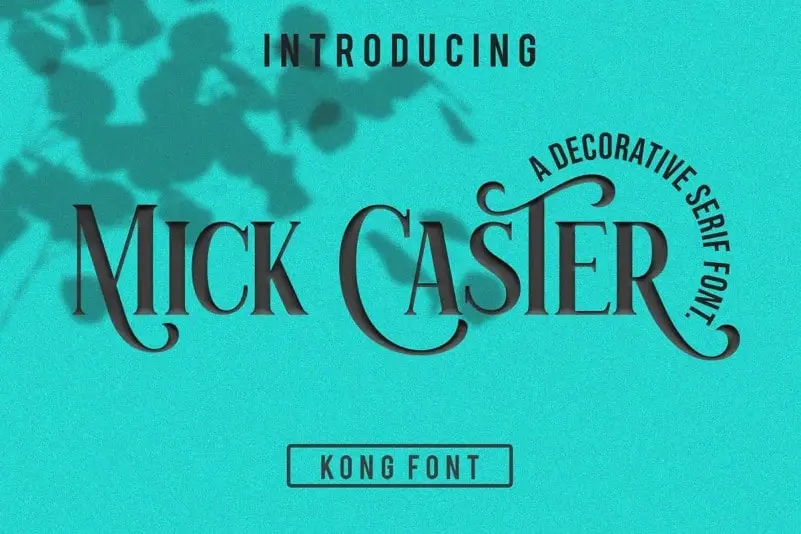
Mick Caster Serif Font – Download Grátis
A Mick Caster Serif Font é uma delícia para os amantes do tipo moderno e vintage, com alternativas estilizadas que brincam com as linhas entre as letras serif. Seu design criativo permite um toque de magia a cada ligatura única, tornando-a uma escolha excepcional tanto para uso no texto quanto para o layout visual. Esta fonte é perfeita para aqueles que buscam algo mais do que apenas uma font tradicional – ela tem as características necessárias para trazer elegância e personalidade ao seu design. Com 99designs como designer, esta Mick Caster Serif Font oferece alternativas estilizadas e ligaturas de corte arredondado que tornam cada palavra um verdadeiro trabalho de arte. E assim, você tem uma fonte que vai destacar em qualquer projeto.